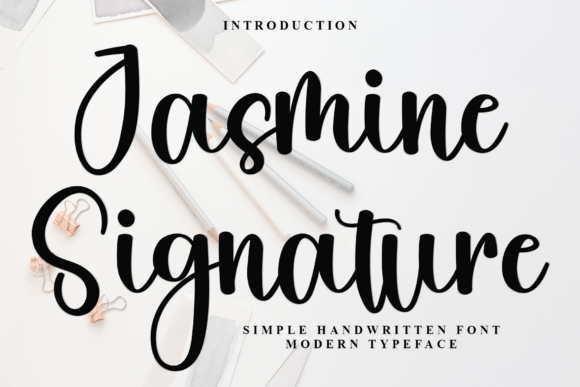
Jasmine Signature
適切なデザイン要素を見つけるのは難しい場合がありますが、Jasmine Signatureは作品を即座に引き立てる優れたコレクションを提供します。
POD(オンデマンド印刷)製品、結婚式の招待状、またはソーシャルメディアのグラフィックを作成している場合でも、Jasmine Signatureは理想的です。